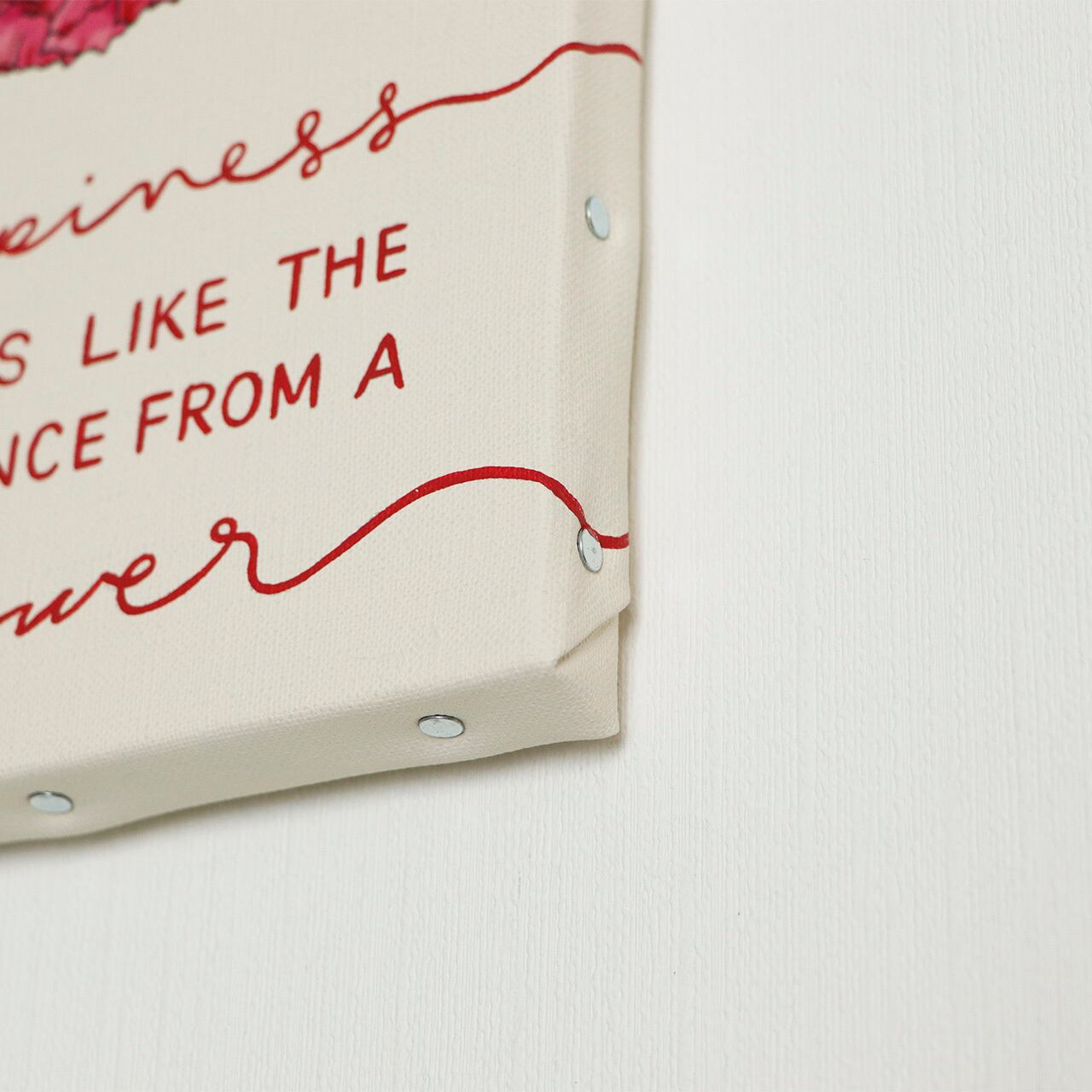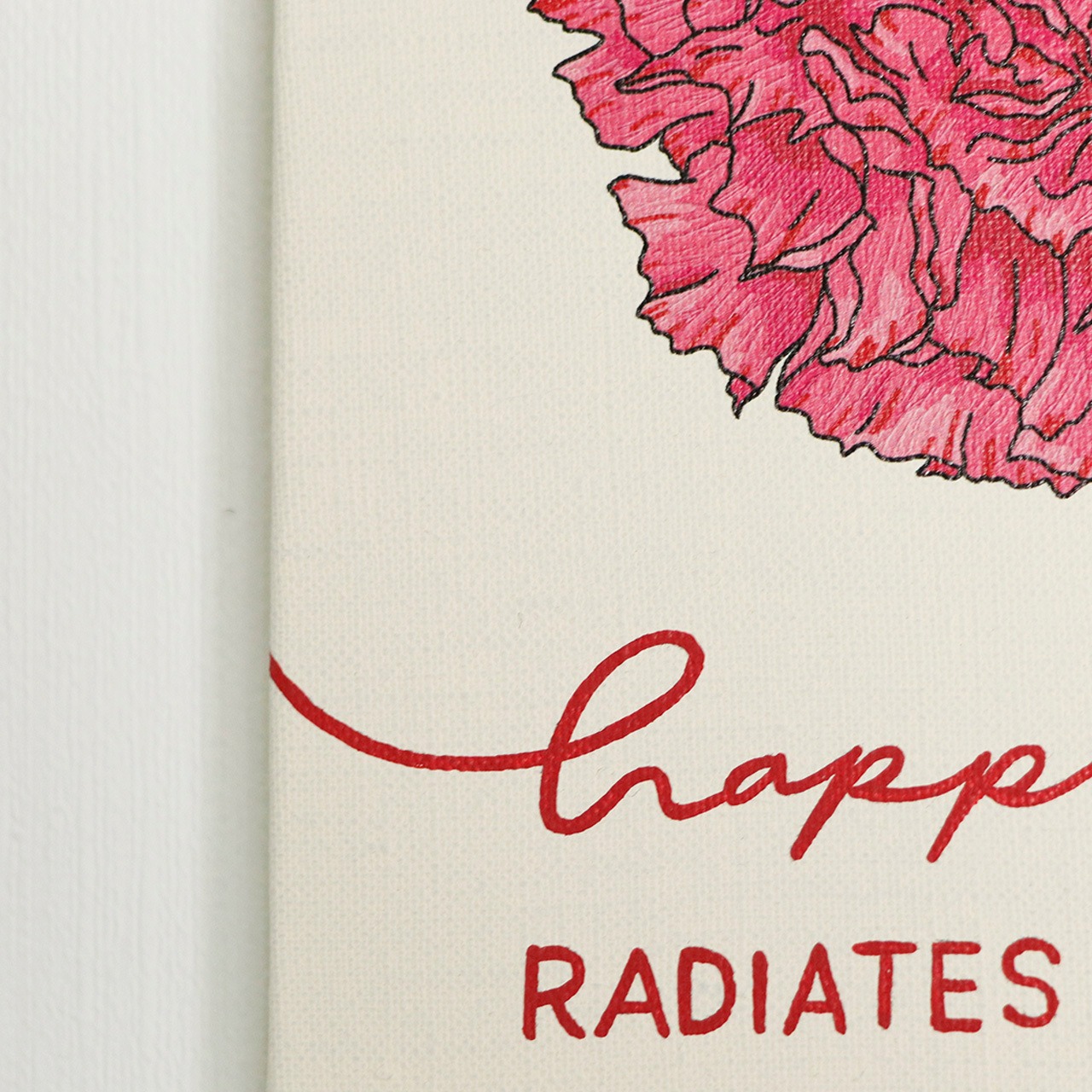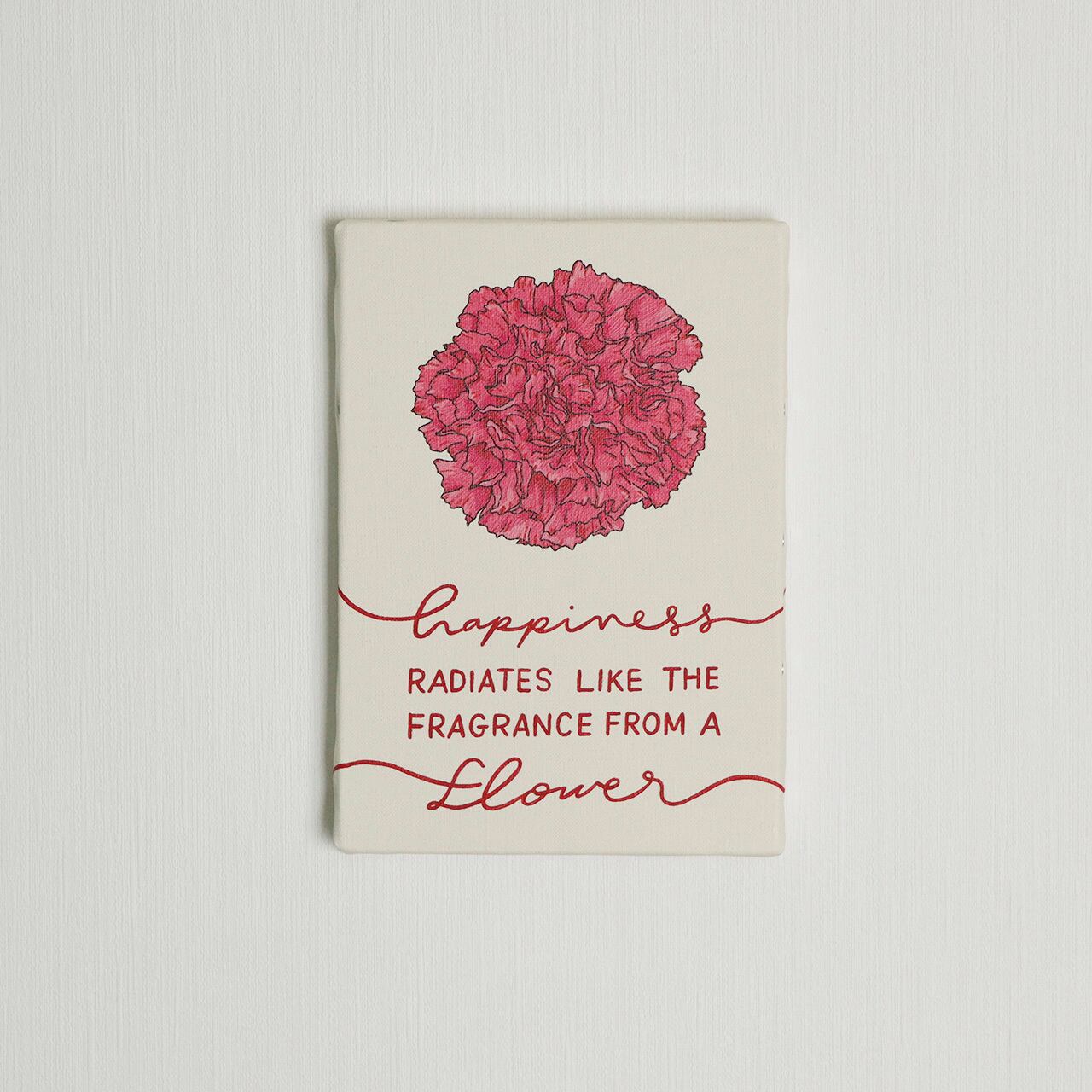
a flower 006 / Happiness radiates like the fragrance from a Flower
一輪の花を摘むように選んでほしい
a flower シリーズ
Happiness radiates like the fragrance from a Flower/幸せは花の香りのように広がる
香りが広がるように、文字もキャンバスの側面に広がっています!